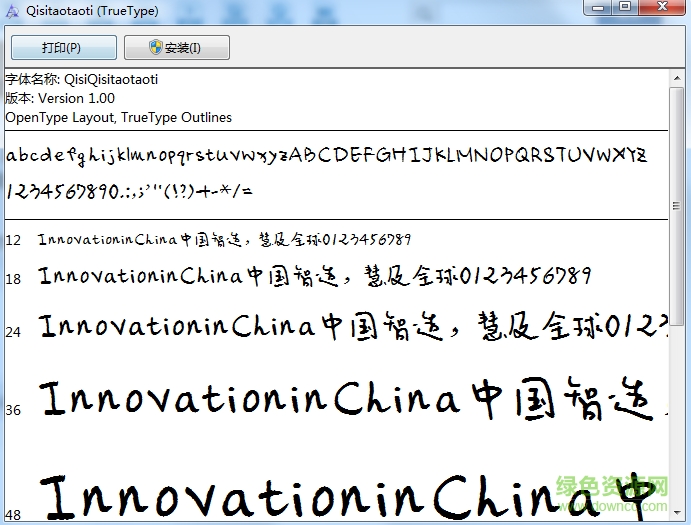
奇思淘淘體是字體管家上的一款藝術(shù)字體,形狀不一的字體樣式給你獨(dú)特的觀賞體驗(yàn),也讓文字變得生動(dòng)活動(dòng)起來(lái),喜歡的朋友就來(lái)綠色資源網(wǎng)下載吧!
字體管家淘淘體是一款字形灑脫的手寫風(fēng)格字體,字體效果流暢、瀟灑得體。適合廣告語(yǔ)、簽名設(shè)計(jì)、海報(bào)設(shè)計(jì)等場(chǎng)合使用。
奇思淘淘體是一款完整不缺字的卡通字體,支持簡(jiǎn)體中文輸入,給大家獨(dú)特個(gè)性魅力的觀看體驗(yàn)!